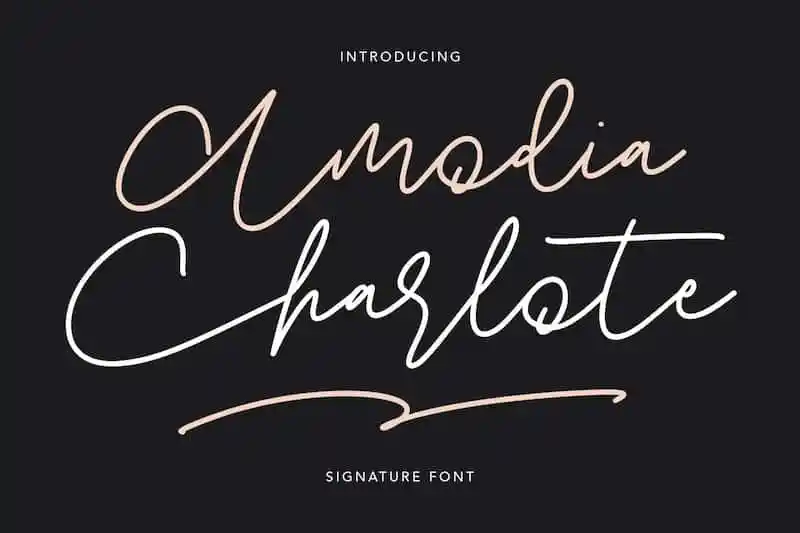
Amodia Charlote Handwritten Font – Download Grátis
Introduzimos Amodia Charlote Handwritten Font, uma elegante fonte escrita à mão que captura a essência do estilo de firma autêntico. Desenvolvida pelo designer Maulana Creative na categoria de fontes script, esta obra-prima se destina para diversos usos criativos. Suas linhas suaves e sutileza fazem dela uma opção perfeita para criações como assinaturas, selos, logotipos, citações em revistas ou livros, cabeçalhos de sites, roupas, marcas de marca, embalagens de produtos e muito mais. Ideal tanto para designers profissionais quanto para iniciantes que desejam adicionar um toque especial a seus projetos digitais e impressos. Descubra o charme de Amodia Charlote Handwritten Font e inspire-se em sua versatilidade.